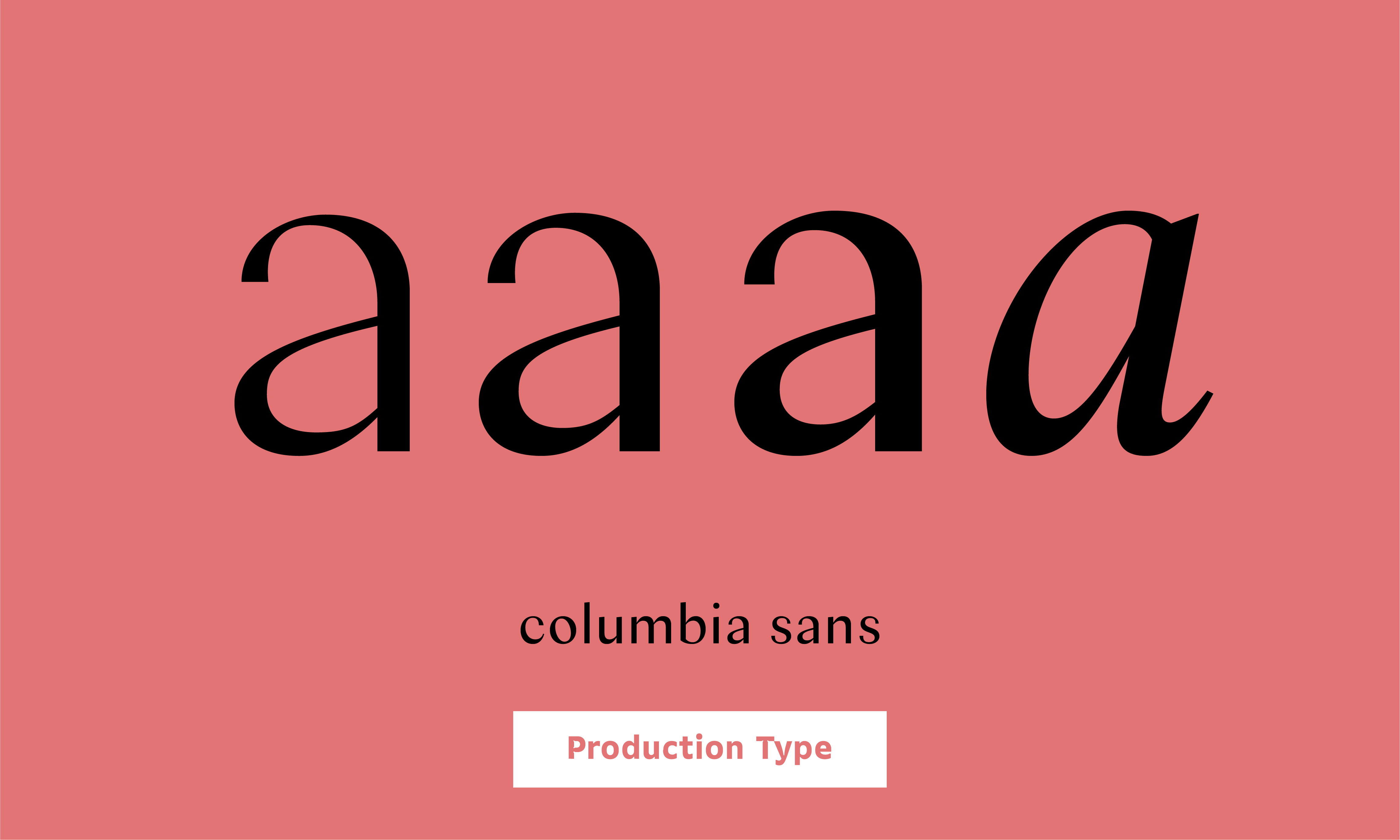
- Columbia는 Tims New Roman의 산 세리프 버전같으면서도 무게중심이 조금 편향되어 있는 폰트이다.
특히 Columbia Sans는 Columbia Sans Disply와는 달리 좁은 x-height와 작은 크기에서도 구분이 가능한 외형을 갖고 있다.
폰트 정보 폰트명 Columbia Sans 구분 고딕 폰트디자인 Jean-Baptiste Levée, Mathieu Réguer, Quentin Schmerber